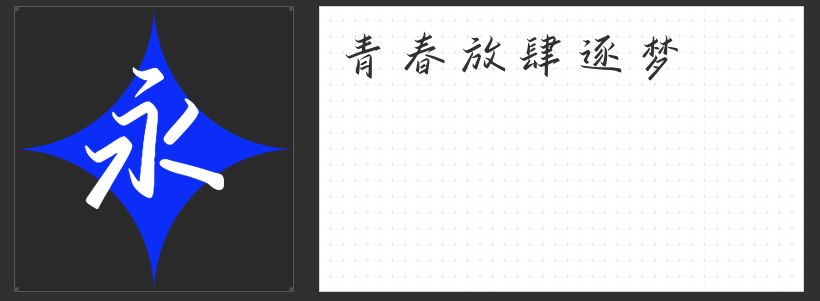
四款风格化字体推荐:以笔触唤醒设计的视觉灵魂
在追求差异化与情感共鸣的设计语境中,字体的选择早已超越“可读性”的基础需求,成为传递品牌气质、强化视觉张力的关键媒介。以下四款各具美学基因的字体,以独特的笔触语言为设计注入灵魂,适配多元场景的创意表达。
一、云书法玉兰行楷体
这款字体以行楷为骨,融汇毛笔书法的气韵与当代设计的简洁感。主笔画粗细对比强烈,块面结构清晰,赋予文字雕塑般的立体层次;牵丝连带自然流畅,如舞者衣袂飘动,既保留传统书法的韵律美,又通过数字化处理提升视觉辨识度。其刚柔并济的特质,使其在文化类海报、高端文创包装中既能传递典雅气质,亦能适配影视娱乐的动态视觉需求。
二、励字造仲夏简 常规
笔画边缘的斑驳肌理与坚挺轮廓形成微妙反差,仿佛墨迹在宣纸与金属间的游走。钩笔的洒脱弧度与横竖笔画的理性直率并存,既保留手写字的温度感,又通过结构优化提升通用性。这款字体尤其适合需要平衡“人文感”与“现代感”的商业场景,如品牌包装的视觉差异化、短视频标题的动态呈现,或新媒体内容中的情绪强化。
三、字青春逐梦简 准粗
以“准粗”字形为基底,笔画末端融入自然收放的笔触变化,既保持字体的端正骨架,又通过微小的不规则感传递松弛氛围。这种“克制中的随性”使其成为标题与内文排版的理想选择——在保证信息高效传递的同时,以视觉的呼吸感营造治愈情绪,适配生活方式品牌、教育类出版物或文艺活动的视觉叙事。
四、造字侠仗剑简繁 传神
折笔如剑出鞘般凌厉,提钩似侠客收势般果断,这款字体以高度凝练的笔画结构演绎“豪侠气韵”。繁简字型的同步设计,使其既能承载传统文化的厚重感,亦能通过夸张的笔画对比强化现代视觉冲击。在需要突出力量感与速度感的设计中,如运动品牌广告、游戏主题海报或动态视觉标题,其戏剧化表现力可瞬间抓住观者视线。
从毛笔书法的东方气韵到手写温度的现代转译,从治愈美学的松弛感到豪侠笔触的戏剧张力,这四款字体以差异化美学语言,为设计提供了超越工具属性的情感表达载体。选择字体,亦是选择一种与受众对话的视觉语言——让笔触成为创意的延伸,唤醒设计的深层共鸣。